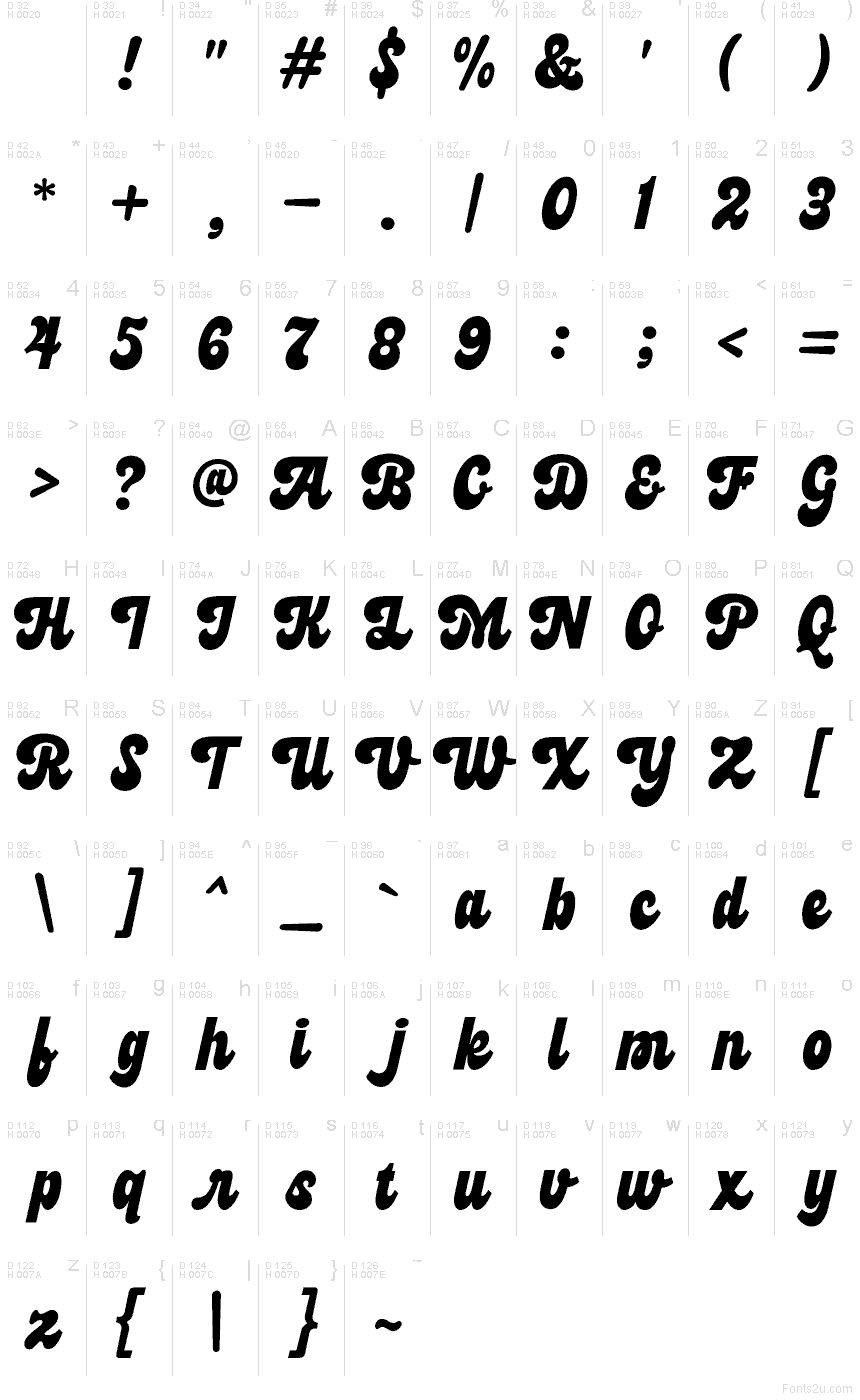
Mister Flavor, de Burhan Afif, é uma fonte gratuita de estilo pincel retrô com a irreverência fácil dos designs de embalagens e música dos anos 70. As letras são espessas, têm um aspecto brilhante e são conectadas de forma compacta, com curvas amplas e junções que lembram gotas, fazendo com que as palavras pareçam ter sido moldadas em vez de escritas.
Ideal para quando um título precisa de calor e um toque de funk: branding de alimentos, menus de cafés, capas de discos, pôsteres e logotipos curtos. Como fonte gratuita, também funciona muito bem em capas, títulos e artes para redes sociais, pois a densidade dos traços e o ritmo das formas carregam muita personalidade mesmo em poucas palavras.